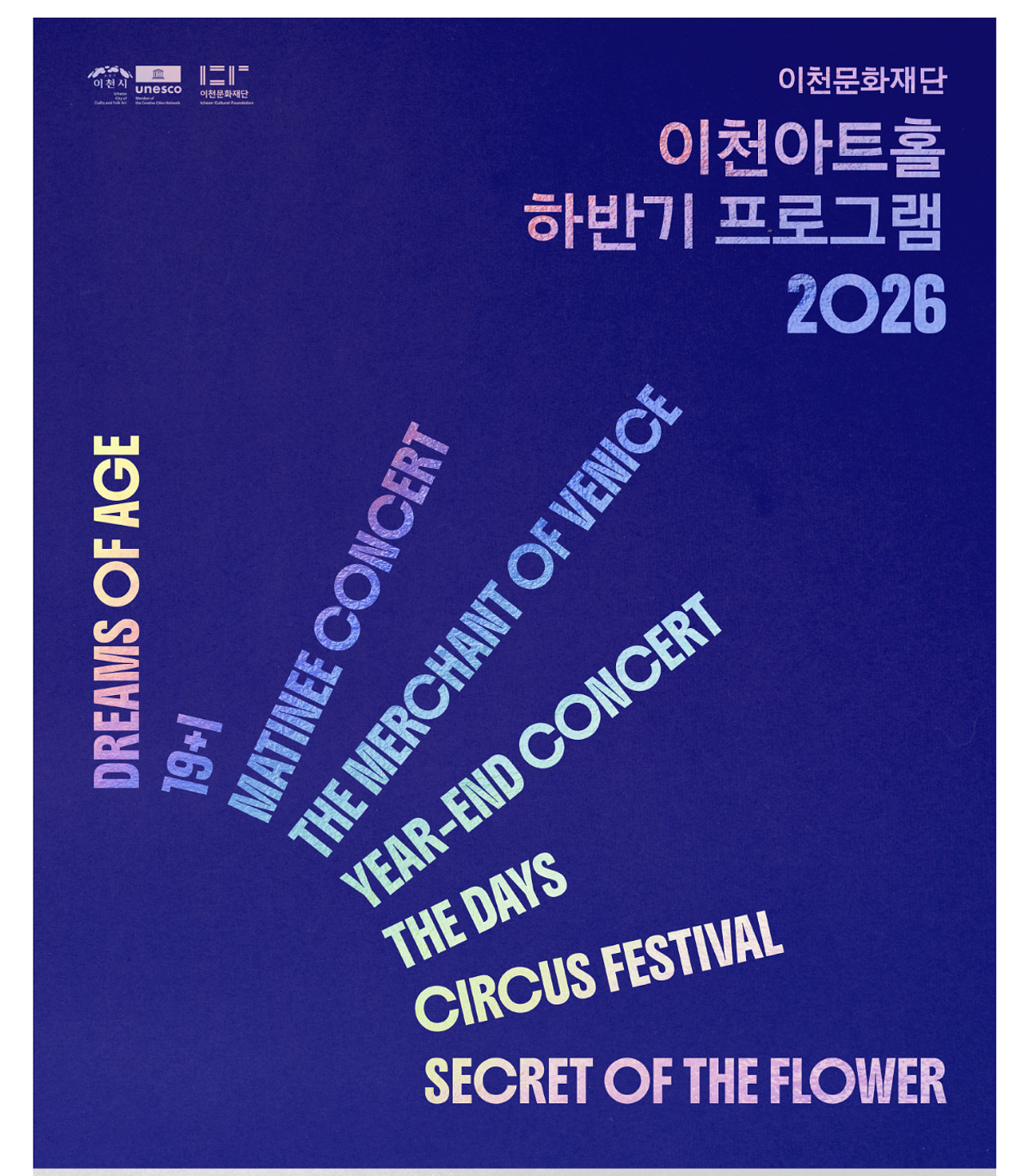
재구언 님의 동영상 중 일부입니다. 한글은 프리텐다드 느낌이고, 숫자는 Gothic A1인 거 같은데 위 처럼 2개 합쳐진 느낌의 폰트는 없을까요?
Sandoll 고딕Neo1
앱이나 프로그램 사용 시 한글 폰트와 라틴 문자가 다른 서체로 렌더링되었을 수 있습니다 국문은 산돌고딕으로 보이네요!